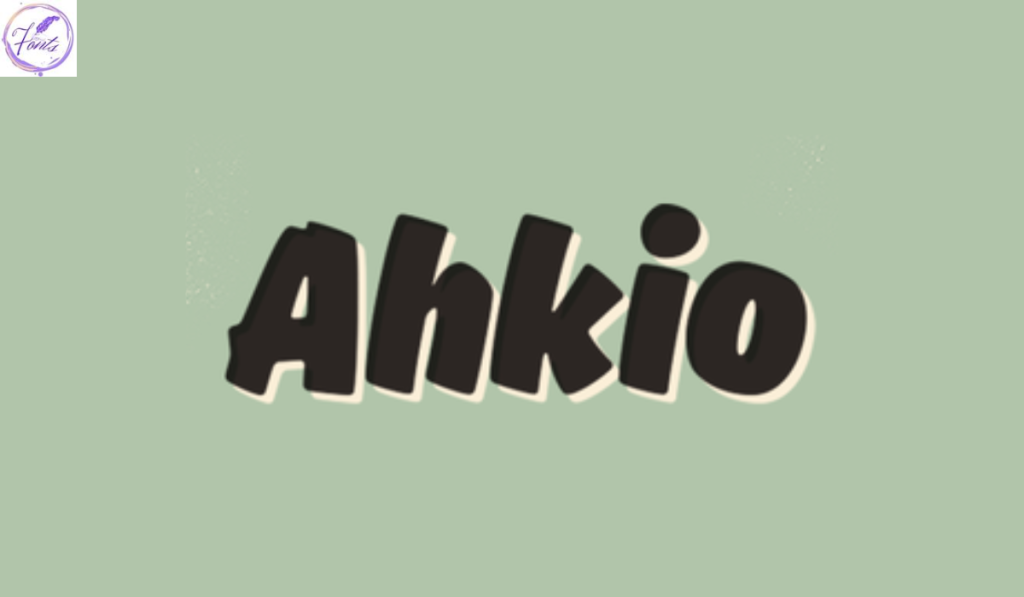
Tác giả: Antti Salli
Ngày phát hành: 2016
Ngôn ngữ: Tiếng Việt, Tiếng Anh, và nhiều ngôn ngữ khác
Bộ Font: Ahkio
Phân loại: Cá tính, độc đáo
Kiểu chữ: Kiểu chữ viết tay
Độ dày: Thin, Light, Regular, Medium, Bold, ExtraBold
Ahkio font free download là một lựa chọn tuyệt vời cho những ai yêu thích phong cách hiện đại và mạnh mẽ. Được thiết kế bởi Antti Salli vào năm 2016, font Ahkio nổi bật với các đường nét đậm, rõ ràng và dễ đọc. Phong cách này rất phù hợp cho các thiết kế như poster, banner, logo, và tiêu đề. Với sự hỗ trợ đa ngôn ngữ, bao gồm cả tiếng Việt, ahkio font free download giúp bạn dễ dàng tạo ra các tác phẩm độc đáo và đầy sáng tạo.
Đánh giá ahkio font free download
Font Ahkio được đánh giá cao bởi tính linh hoạt và khả năng ứng dụng rộng rãi. Người dùng đánh giá cao font này vì nó mang lại sự mạnh mẽ và hiện đại cho bất kỳ thiết kế nào. Ngoài ra, Ahkio còn có tính năng ligature và alternative characters, giúp tạo nên những văn bản sáng tạo và thú vị hơn. Sự kết hợp giữa tính thẩm mỹ và tính thực dụng khiến Ahkio trở thành một lựa chọn lý tưởng cho các dự án thiết kế đòi hỏi sự chuyên nghiệp và sáng tạo.